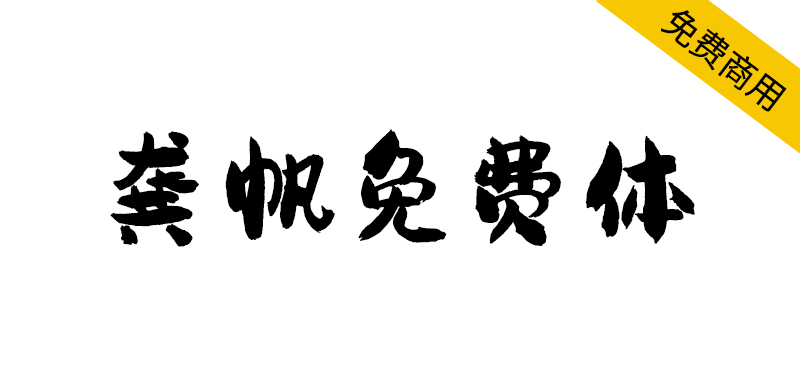
【龚帆免费体】视觉坊出品,高质量毛笔字体
龚帆免费体是龚帆字库发布的一款免费可商用的高质量毛笔字体,可供全社会个人与企业免费商用,字库包含4005常用字符,适用范围非常广。龚帆免费体有着很明显的手写痕迹,毛笔的笔触非常明显,提笔收笔的质感在字体上也能清晰看出。字体整体字形比较圆润,笔划相对比较随性,弯曲较多,字体转折处也没有很锋利的棱角,这些特征使它更具一分亲和感。可用于包装、电商、漫画、影视综艺、游戏、各类商业海报、户外广告标题等。